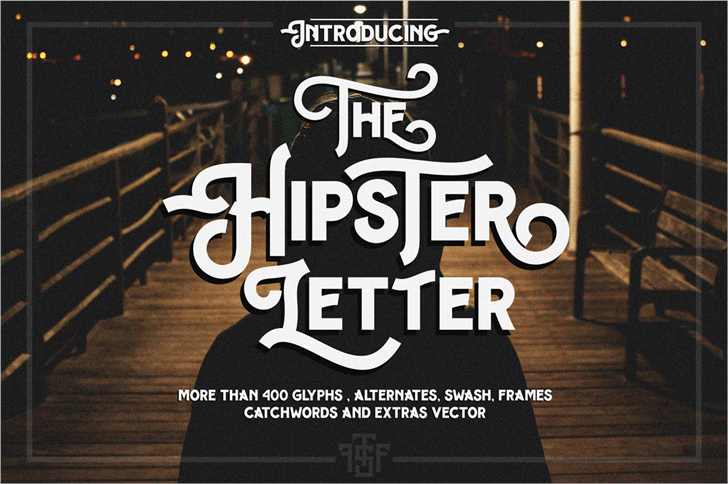
Hipster letter Font – Fonte Grátis
Hipster letter Font
A nova fonte de exibição Hipster Letter foi criada por Hamilton. Inspirada nas tipografias modernas e na escrita moderna, a fonte Hipster Letter é uma fonte capital com curvas simples e atemporais, oferecendo muitas alternativas para criar designs incríveis. Possui mais de 400 caracteres, incluindo conjuntos estilísticos, ligaduras, alternâncias contextualizadas e alguns extras. A fonte Hipster Letter é perfeitamente adequada para aplicações como cartazes, logotipos, assinaturas de carta, títulos, marcação, embalagens e tipografia. Inspirada no design da Typografi e na letra moderna, a Hipster Letter oferece uma aparência atraente e elegante. Ideal para quem busca um visual único e criativo em seus projetos gráficos.